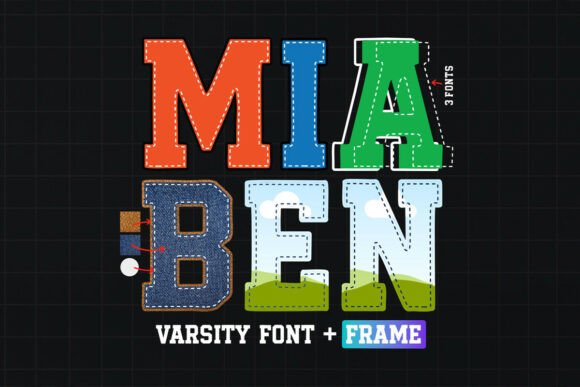
Mia Ben Canva Font Frame Template
Việc tìm kiếm các thành phần thiết kế phù hợp có thể là một thách thức, nhưng Mia Ben Canva Font Frame Template cung cấp một bộ sưu tập đặc biệt giúp nâng tầm công việc của bạn ngay lập tức.
Được chế tác với độ chính xác cao, Mia Ben Canva Font Frame Template cung cấp các vector sạch, kiểu chữ mượt mà và giấy phép thương mại để bạn yên tâm.